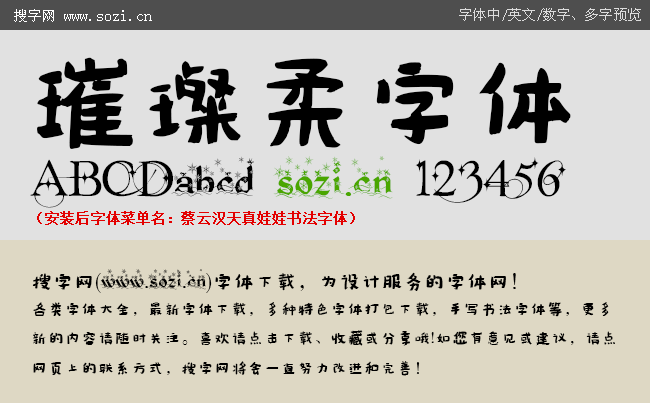
璀璨柔字體
搜字網(wǎng)給大家提供一款璀璨柔字體手機(jī)中文字體下載。這款手機(jī)字體是以蔡云漢天真娃娃書法字體為原形,數(shù)字和英文部分加入了卡通花紋的裝飾,是一款融合了現(xiàn)代卡通書體風(fēng)格的中文漢字,在具有卡通幾格的同時(shí),又兼具書法韻味,喜歡的朋友快快下載吧。